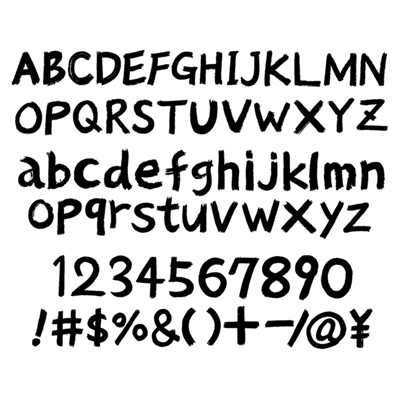
筆で書いたよfont
筆の毛先から生まれたフォント!
Artistmassu(まっすー)
Designerさとうひろゆき
Organizationあそ美
子どもの頃から書に親しんでいました。筆先の毛の感じを自由に遊ぶように書いてみました。(massu(まっすー))
筆先のかすれた感じがカッコいいフォントです。外国の方にも使って欲しいです。(さとうひろゆき)
水墨画的な書き方をいつも探究しています。筆先のかすれ具合を感じながら使用して欲しいです。(あそ美)